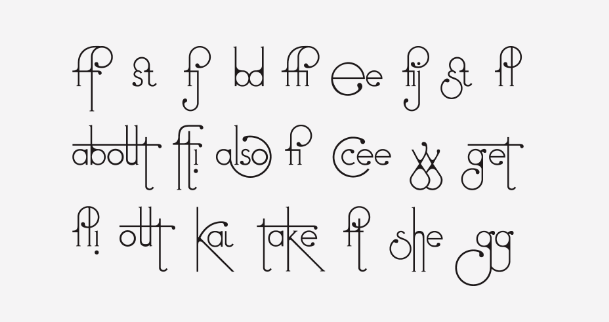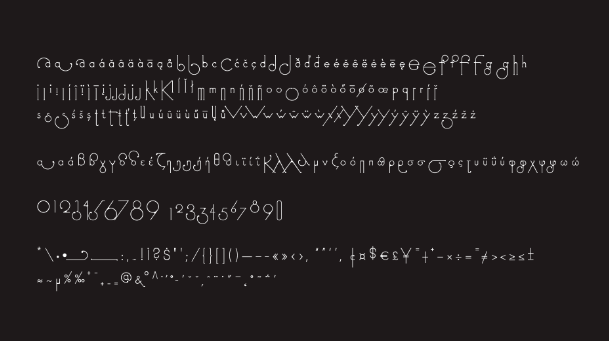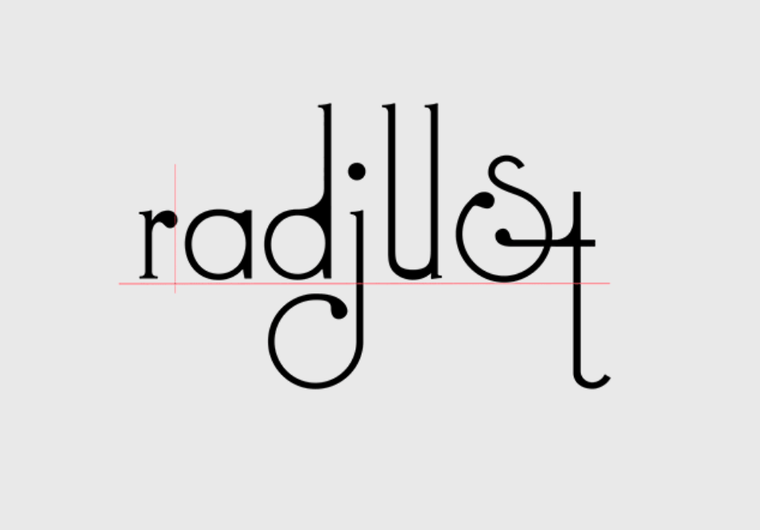
La original tipografía que cambia según se escribe el texto
Casi todas las palabras que leemos están escritas en una fuente creada por un artista, un equipo de ellos o incluso varias generaciones de diseñadores. Para los no iniciados en este mundillo, que interactúan con los distintos tipos de letra sin pensar más allá, sus posibilidades no parecen particularmente interesantes. Futuracha Pro está a punto de cambiar eso, según lo cuenta El Huffington Post.
Escribir con Futuracha Pro, diseñada por Odysseas Galinos Paparounis, de la agencia griega høly, no es una experiencia estática y predecible. La fuente responde al contexto, cambiando entre distintos diseños dependiendo de la composición de cada palabra. Es camaeleónica y resulta fascinante verla en acción.
La fuente es una versión de la fina Futura embellecida con inspiración art déco está inspirada por una insospechada musa: la cucaracha del Caribe.
Según contó Paparounis por email a la edición estadounidense del HuffPost, Futura se había convertido en "algo así como una obsesión" para él mientras estudiaba diseño gráfico. Cuando le encargaron que creara una tipografía en una asignatura, se inspiró en dos cucarachas del Caribe que observaba para una clase de ilustración. Inspirado por "las antenas y los pinchos de sus pies", adornó el armazón de Futura con remates redondeados y ligaduras.
De este modo nació Futuracha, un juego de palabras entre Futura y cucaracha. "Se podría decir que es una fuente sans serif [sin remates] que se ha transformado en una serif [con remates] en un estado de ánimo de exageración", añadió su creador.
Inicialmente esta tipografía -que tenía numerosas variaciones de letras para permitir distintas combinaciones- sólo estaba disponible en un formato que requería el posicionamiento individual de las letras en una interfaz de diseño gráfico. Gracias al impulso de un crowdfunding eso va a cambiar con el lanzamiento de Futuracha Pro, una fuente de uso libre con la que sus usuarios podrán escribir.
Futuracha Pro no es la primera fuente que se va ajustando según se escribe, pero va un paso más allá de lo habitual. "La mayoría se aprovechan de ligaduras y adornos en un intento de corrección visual", explicó Paparounis. "Futuracha, por su parte, no sólo tiene adornos, sino una gran variedad de ellos para elegir. Coloca la creatividad junto a la funcionalidad, el juego antes de las instrucciones y la experimentación antes que los manuales".